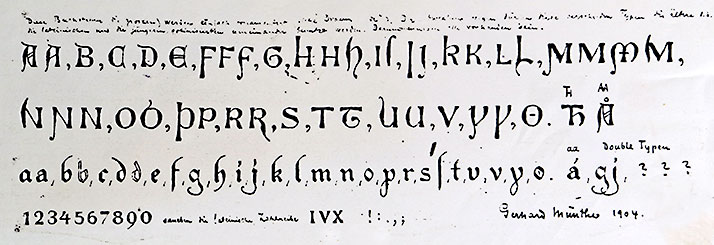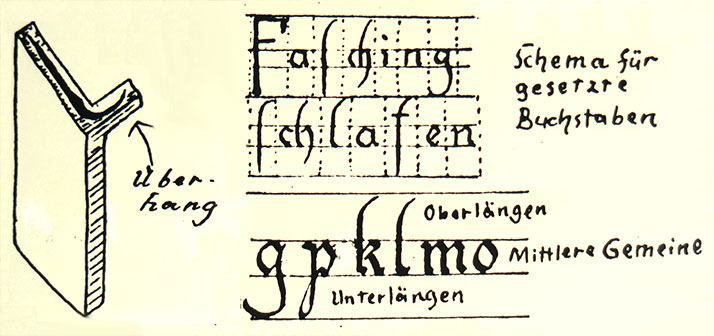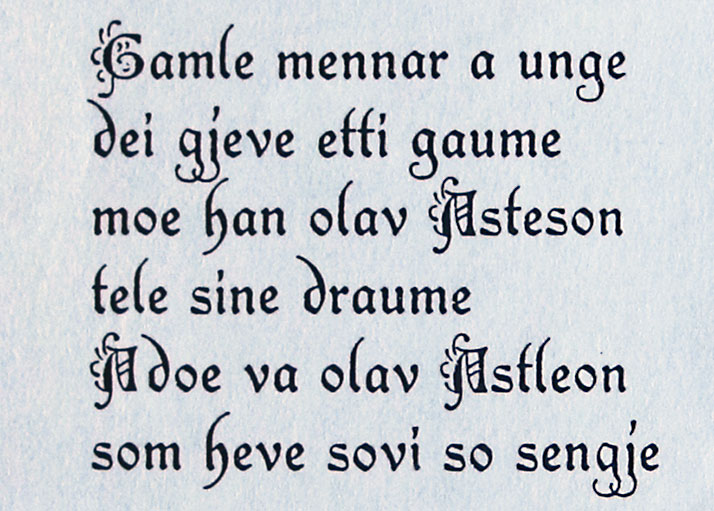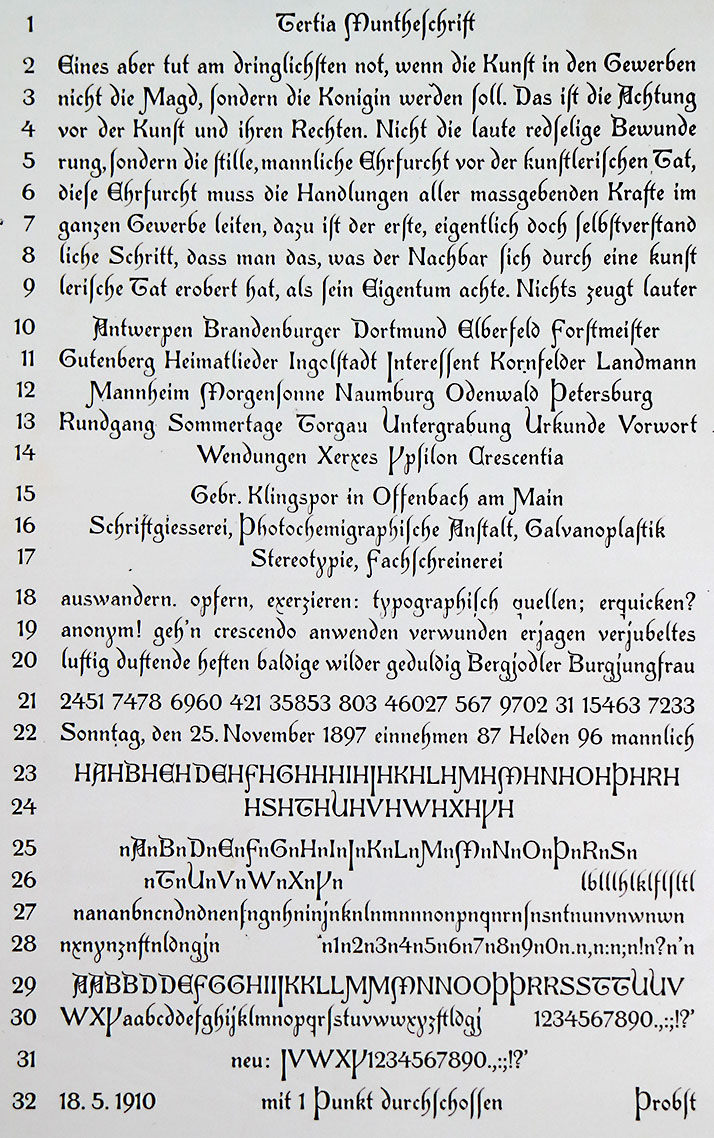
Bokvenner husker vel Gerhard Munthe (1849–1929) helst som en av illustratørene av Snorre Sturlassons Kongesagaer, utgitt første gang i 1899. Draumkvæde fra 1904, der han sto for bind, illustrasjoner og den håndtegnede tekst, er et annet betydelig bokkunstnerisk arbeid fra Gerhard Munthes hånd. Bokas særegne skrift førte ham inn i et mangeårig samarbeid med et tysk skriftstøperi, med formål å lage en gotisk trykkskrift egnet til utgivelse av nordiske middelalder-manuskripter.
Historien om arbeidet med å lage en «Muntheskrift», og Oslo-trykkeriet Fabritius' forsøk på det samme tretti år seinere, er fra en bokhistorisk synsvinkel av stor interesse. Denne historien har inntil nylig vært udokumentert. (Denne artikkelen ble skrevet i 1995.)
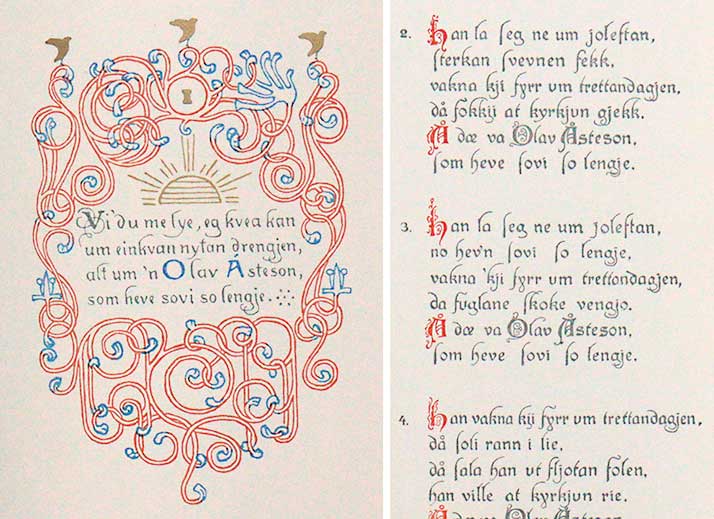
Til venstre det første verset i Draumkvæde, der noen av bokstavene er utformet noe ulikt de øvrige versene. V, O og A har alle antikva-karakter i dette verset. Til høyre de tre påfølgende versene, der O og A har gotisk karakter, og også er sterkt dekorert. De små bokstavene i versene 2, 3 og 4 er også mer elegant utformet enn i det første verset. Jeg tror at det første verset er tegnet av Munthe personlig, mens August Sørensen sto for de øvrige.
Ingen framstillinger av norsk bokhistorie har kommet utenom Munthes Draumkvæde-utgivelse fra 1904. Fra ytterst til innerst er det en særpreget publikasjon, som er blitt karakterisert som et kunstverk mer enn en bok. (Se alle sidene i Draumkvæde her.)
Bindet er en pergamentimitasjon, med innmonterte blå glassperler, utført av H. M. Refsum. Reproduksjonen av Munthes illustrasjoner var et pionerarbeid i Skandinavia. Firmaet Wilh. Scheel måtte hente inn en utenlandsk fagmann for å fargeseparere akvarellene, som ble trykt med opptil seks farger, deriblant gull. Teksten er håndtegnet med en rikt dekorert gotisk skrift, utført av tegneren Aug. Sørensen etter Munthes anvisninger. Oslo-trykkeriet W. C. Fabritius & Sønner sto for trykkingen. Boka består av 15 blad og ble trykt i ca. 300 eksemplarer. De aller fleste gikk til medlemmene av «Forening for norsk bokkunst», som var utgiver.
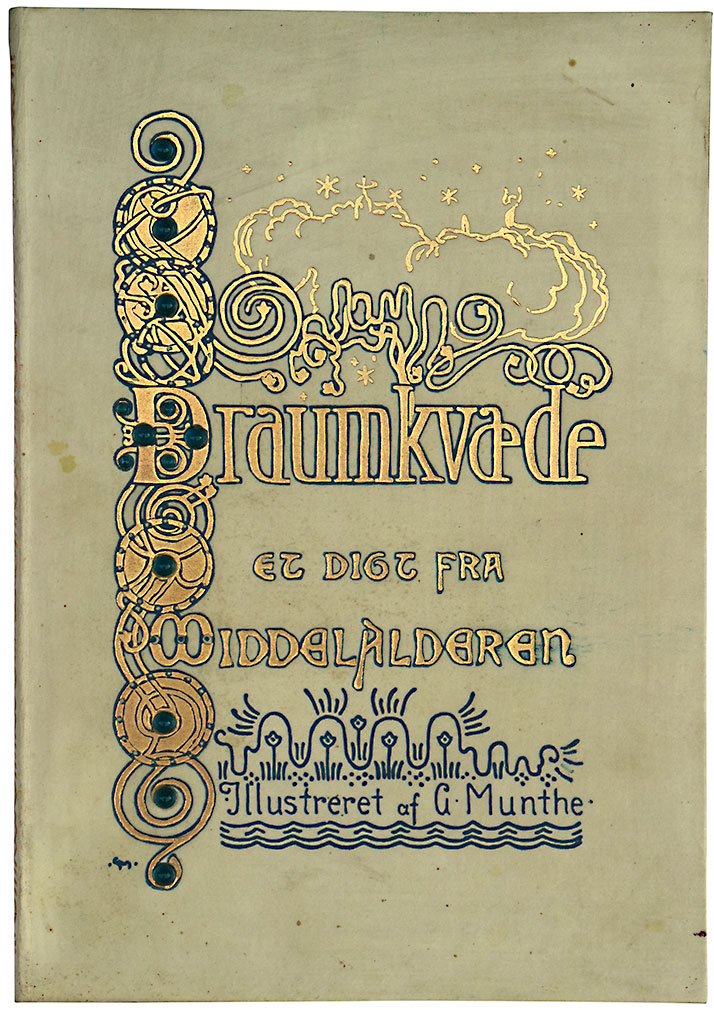
Bindet i Gerhard Munthes Draumkvæde er laget av imitert pergament og utført av hoffbokbinder H. M. Refsum i Christiania. Munthe bestilte de blå glassperlene fra Tyskland. Ifølge kritikerne den gang hadde de en tendens til å falle ut, men de er fortsatt på plass i mitt eksemplar, også på bindets bakside.
Arbeidet for å heve nivået på boktrykket
Rundt århundreskiftet ivret mange for et tettere samarbeid mellom kunstnere og håndverk og industri. Engelskmannen William Morris var en foregangsmann. Påvirket av hans innsats for å reformere boken gjennom sitt trykkeri Kelmscott Press (1891–1896), ble det i mange land arbeidet for å heve nivået på boktrykkerkunsten.
Forening for norsk bokkunst ble stiftet år 1900. I samsvar med den nasjonale stemning i årene fram mot unionsoppløsningen valgte man som sin første publikasjon å utgi Draumkvedet, et verk som man anså for å være ekte norsk, og ikke vandret inn fra utlandet – som andre folkeviser.
Inngangsfrisen til Harald Haardraades Saga i Snorre (1899) – et av mange elementer i dette bokverket som Gerhard Munthe sto bak.
Etter utgivelsen av Snorre i 1899 var Gerhard Munthe etablert som Norges mest betydelige bokkunstner. Han hadde i mange år arbeidet med en særegen norsk dekorativ kunst. Han pekte seg ut som den som best kunne illustrere den mystiske, religiøse Draumkvedet-visen for den nystartet bokkunstforeningen, der han også var styremedlem.
Opprinnelig var planen å utgi diktet og illustrasjonene sammen med en forklaring av Draumkvedet, som folkloristen Moltke Moe skulle forfatte. Men mens Munthe kunne vise fram illustrasjonene på et medlemsmøte i bokkunstforeningen allerede i februar 1901, trekvart år etter stiftelsen, lot Moes forklaring vente på seg. Han fikk stadig forlenget sine frister, mens Munthes utålmodighet vokste.
Omsider bestemte man seg for at Moltke Moes tekst skulle utgis separat på et senere tidspunkt. I desember 1904 var Draumkvæde endelig ferdig. Den vakte stor oppsikt både i inn- og utland, og er blitt både beundret og kritisert, et engasjement som har vart helt opp mot våre dager.
Skriften i Munthes Draumkvæde
Den tegnede teksten ble av noen vurdert som et blindspor, i betraktning av at bokkunstforeningen ifølge sitt formål skulle utvikle bokhåndverket. Typografen var jo satt helt til side! Styret besvarte kritikken med å slå fast at foreningens neste publikasjon skulle bli et rent typografisk produkt.
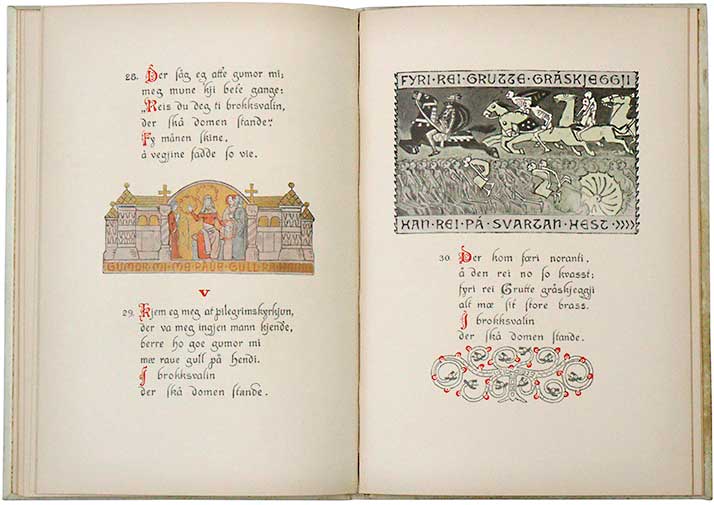
Et oppslag i Draumkvæde, som består av til sammen 51 vers.
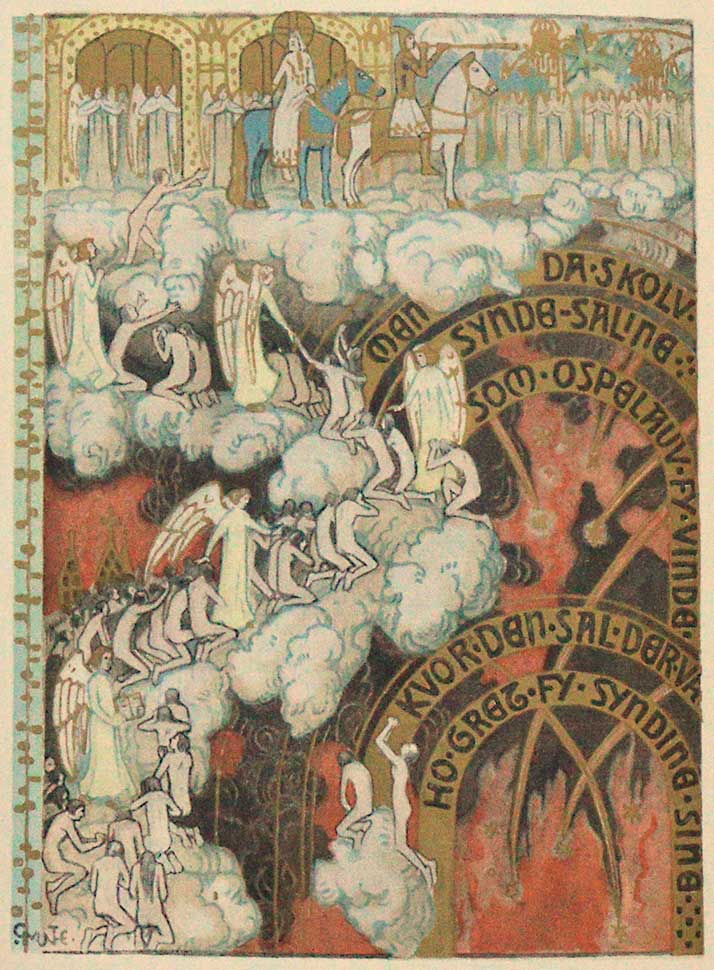
«Dommedag»-illustrasjonen i Draumkvæde.
Skriften i boka var basert på Munthes kjennskap til nordiske middelalderhåndskrifter fra det 13. århundre, og på sagahåndskriftet Codex Frisianus spesielt. Denne boka, som siden 1600-tallet har befunnet seg i Danmark, er høyt vurdert for sin vakre skrift og mange store, fargede initialer.
Draumkvæde-skriften er gotisk, der overlengder og underlengder er forsynt med lange, kalligrafiske utløpere (f.eks. f og j). Enkelte bokstaver er høyst originale (f.eks. p). De store bokstavene er ornamentert, inspirert av initialene som innleder kapitler og avsnitt i middelalderhåndskriftene, og er trykt i rødt. Som middelalderhåndskriftenes initialer er de store bokstavene av ulik karakter: noen er antikvaer, mens andre har gotiske former.
Et utsnitt av Gebr. Klingspors Munthe-Schrift, datert 1910.